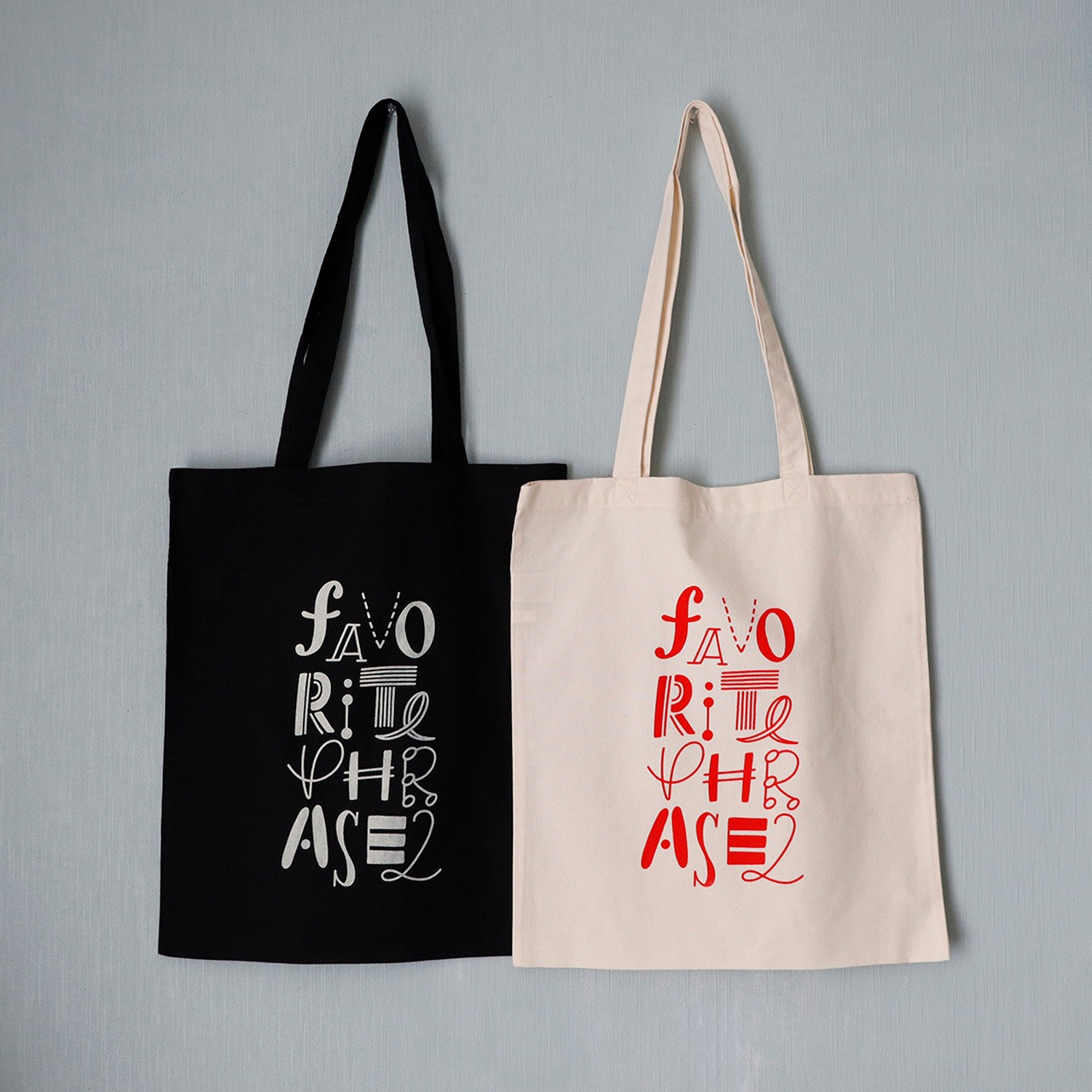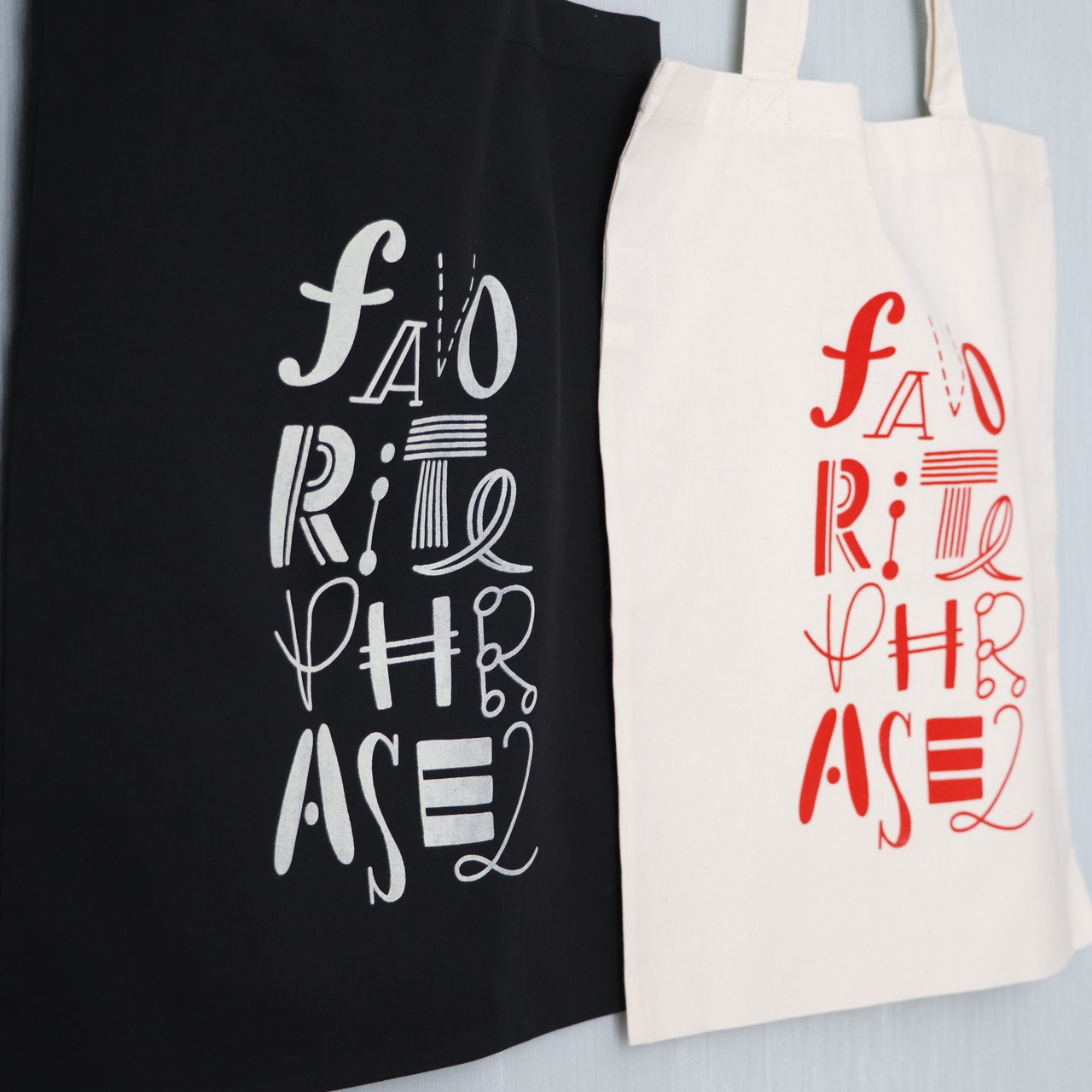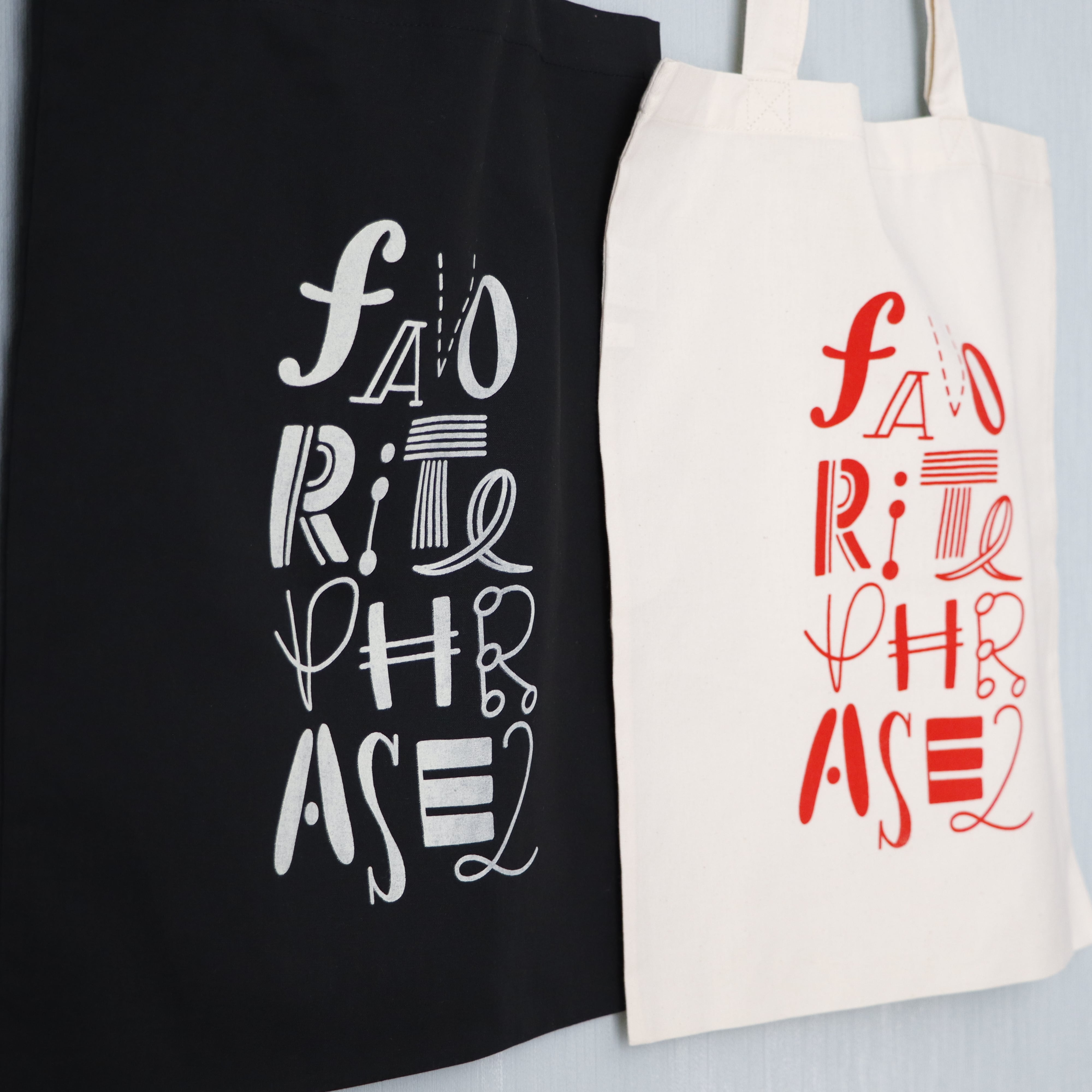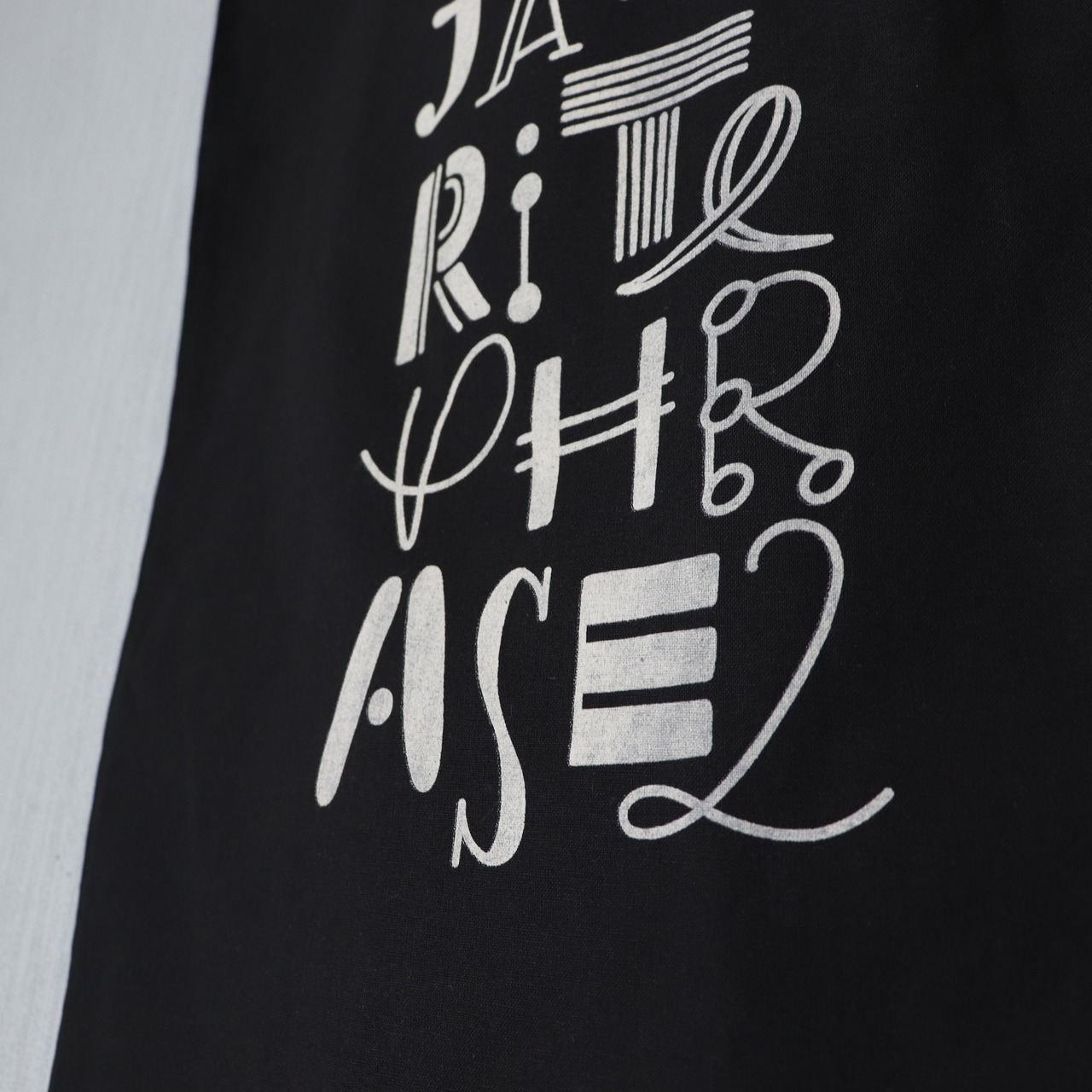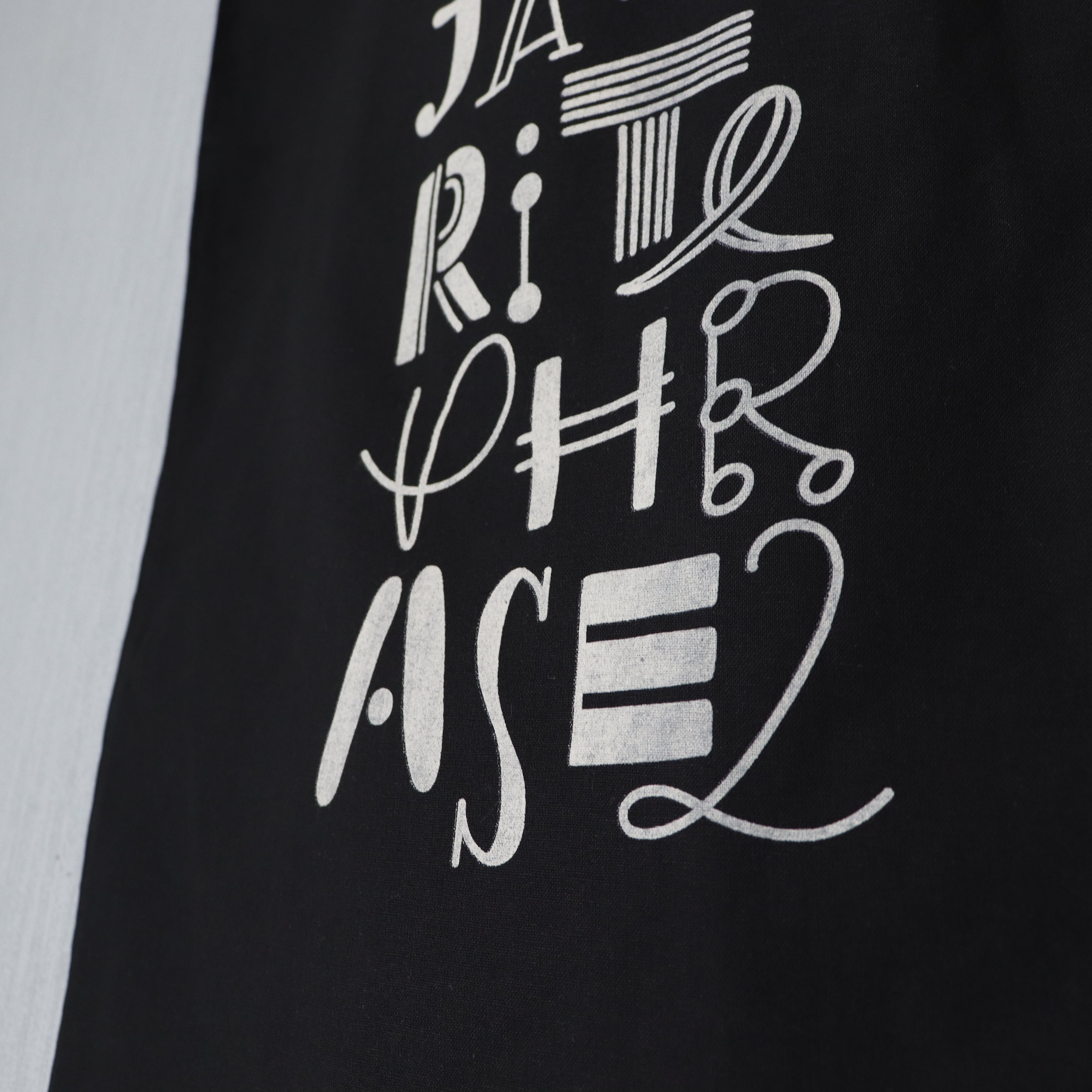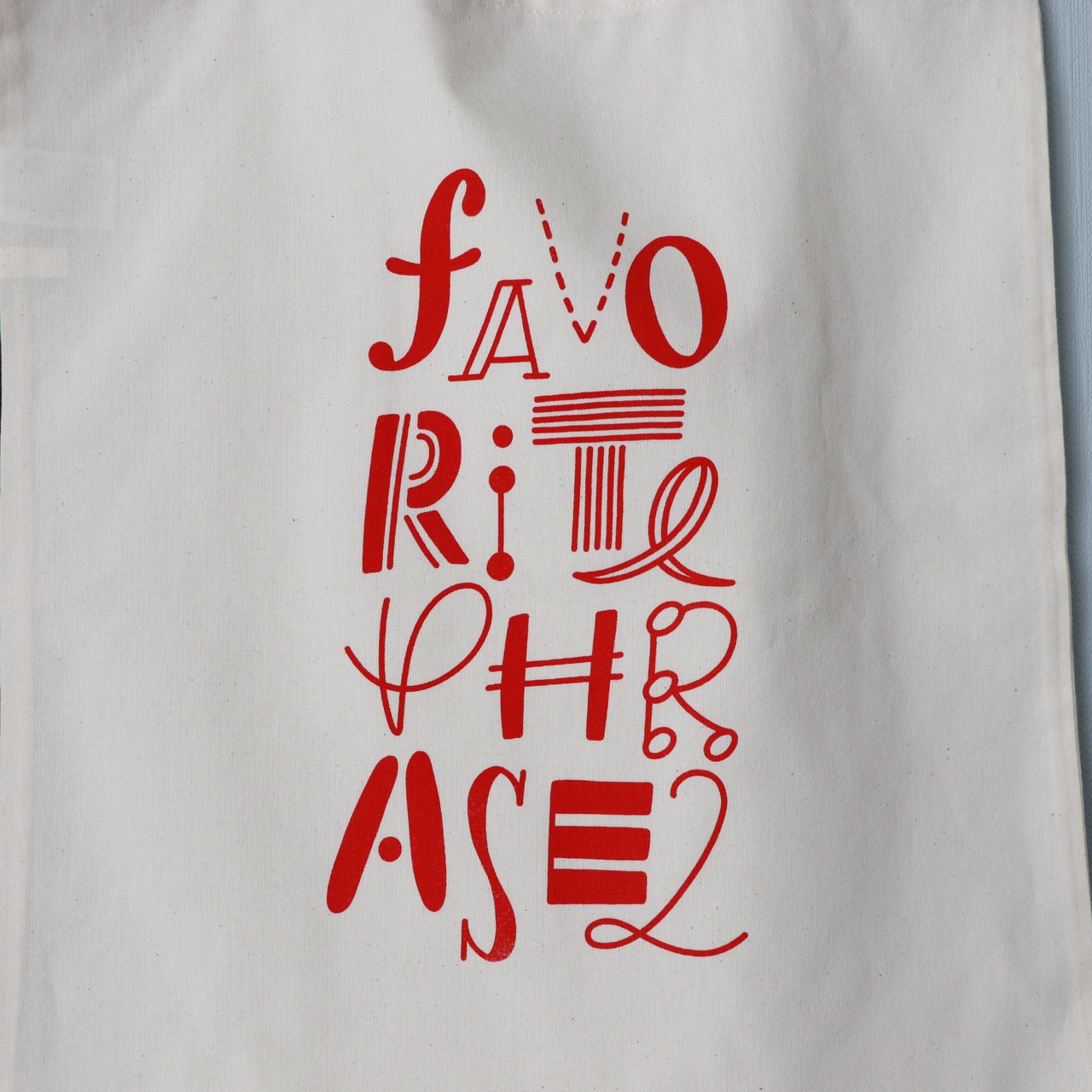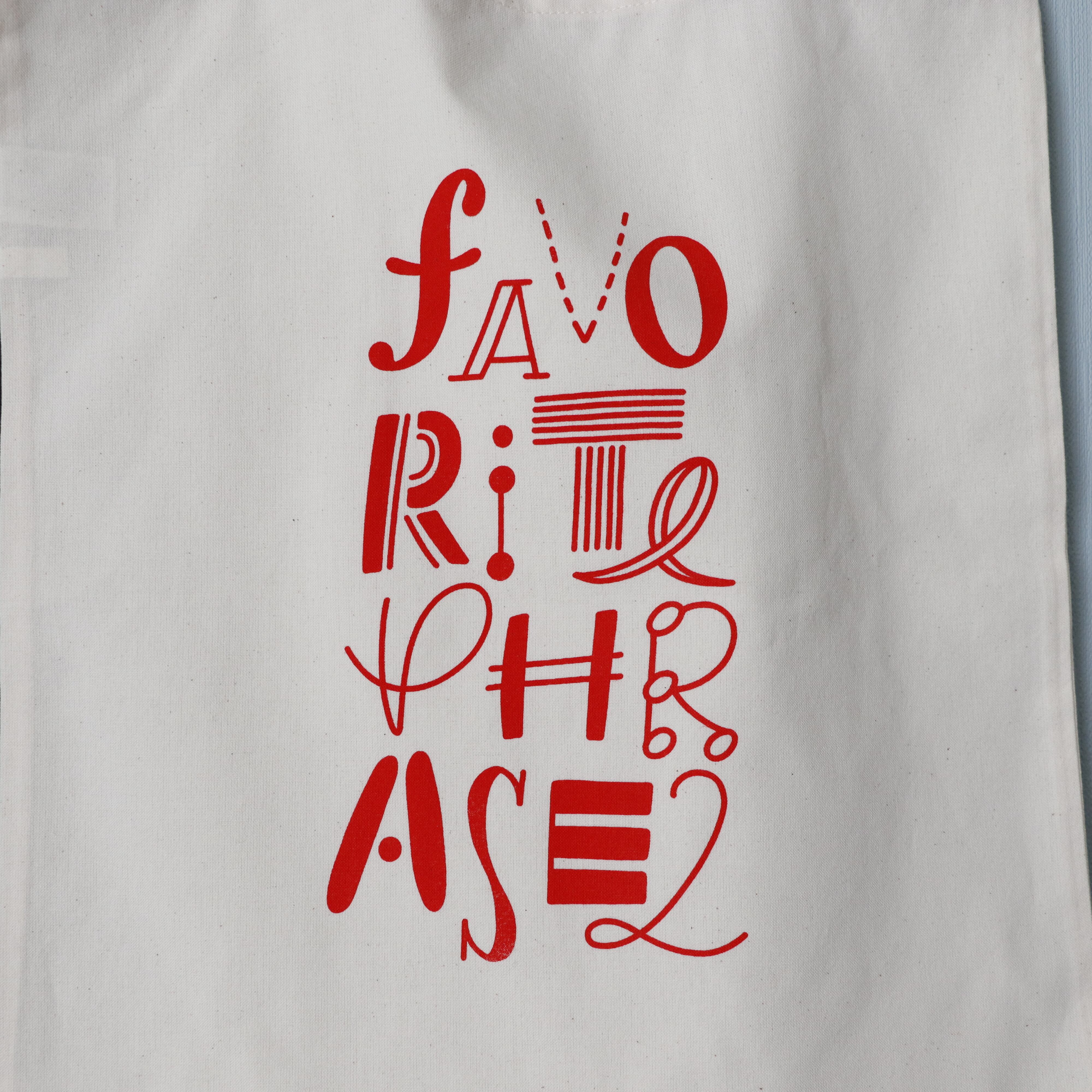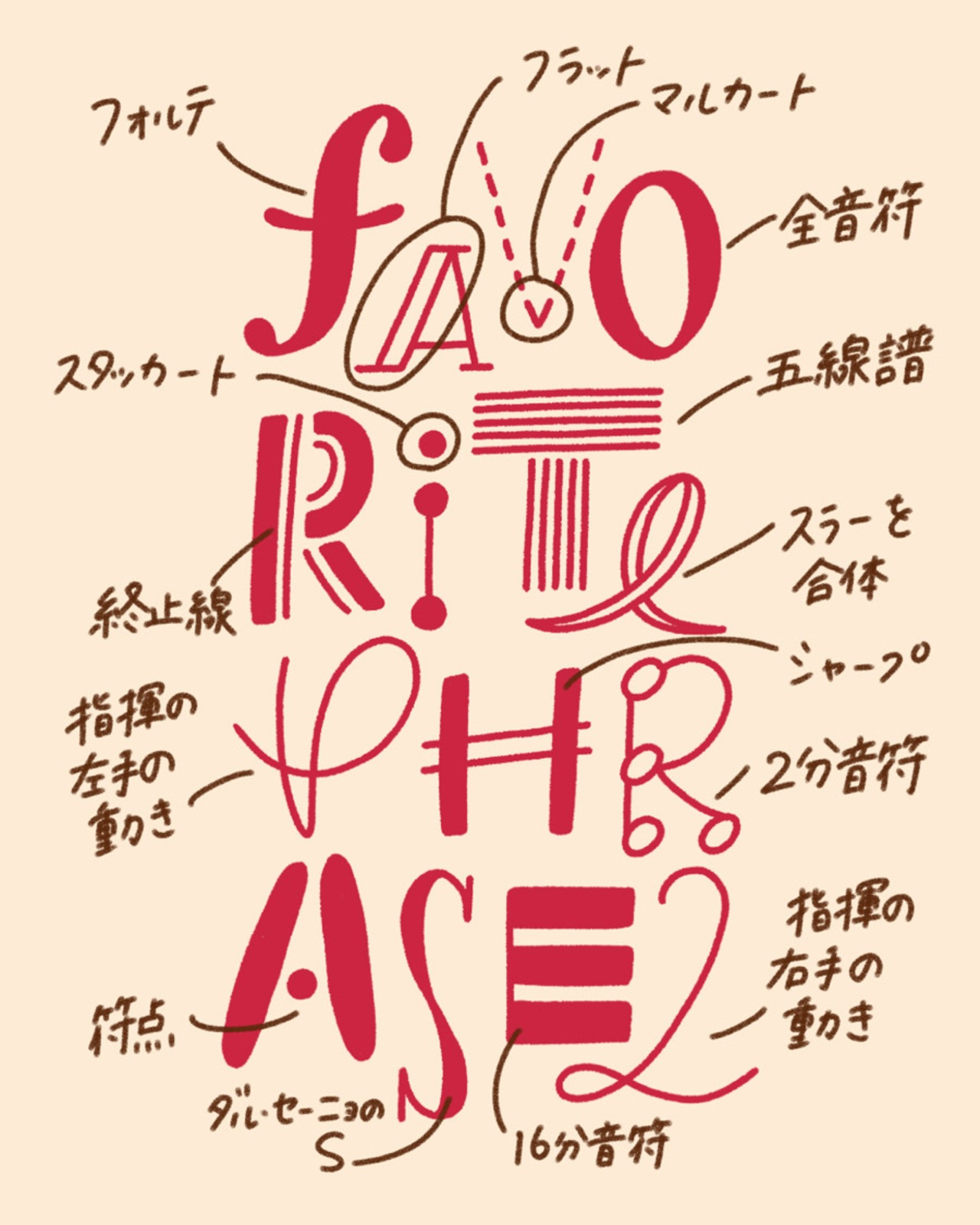
FAVORITE PHRASE2トートバッグ(アイボリー/ブラック)
2026年個展「FAVORITE PHRASE2」のメインビジュアルがトートバッグになりました!
PHRASEは「言葉のフレーズ」以外に「音楽のフレーズ/旋律」の意味でもあります。
全フォント、音楽と楽譜をモチーフにしたものになっています。
音楽やってる方、ぜひ答え合わせしてみてください♪
一点ずつシルクスクリーンで手刷りしています(私が!!!)
そのため若干のかすれなどがありますが、手刷りの「味」として楽しんでもらえると嬉しいです。